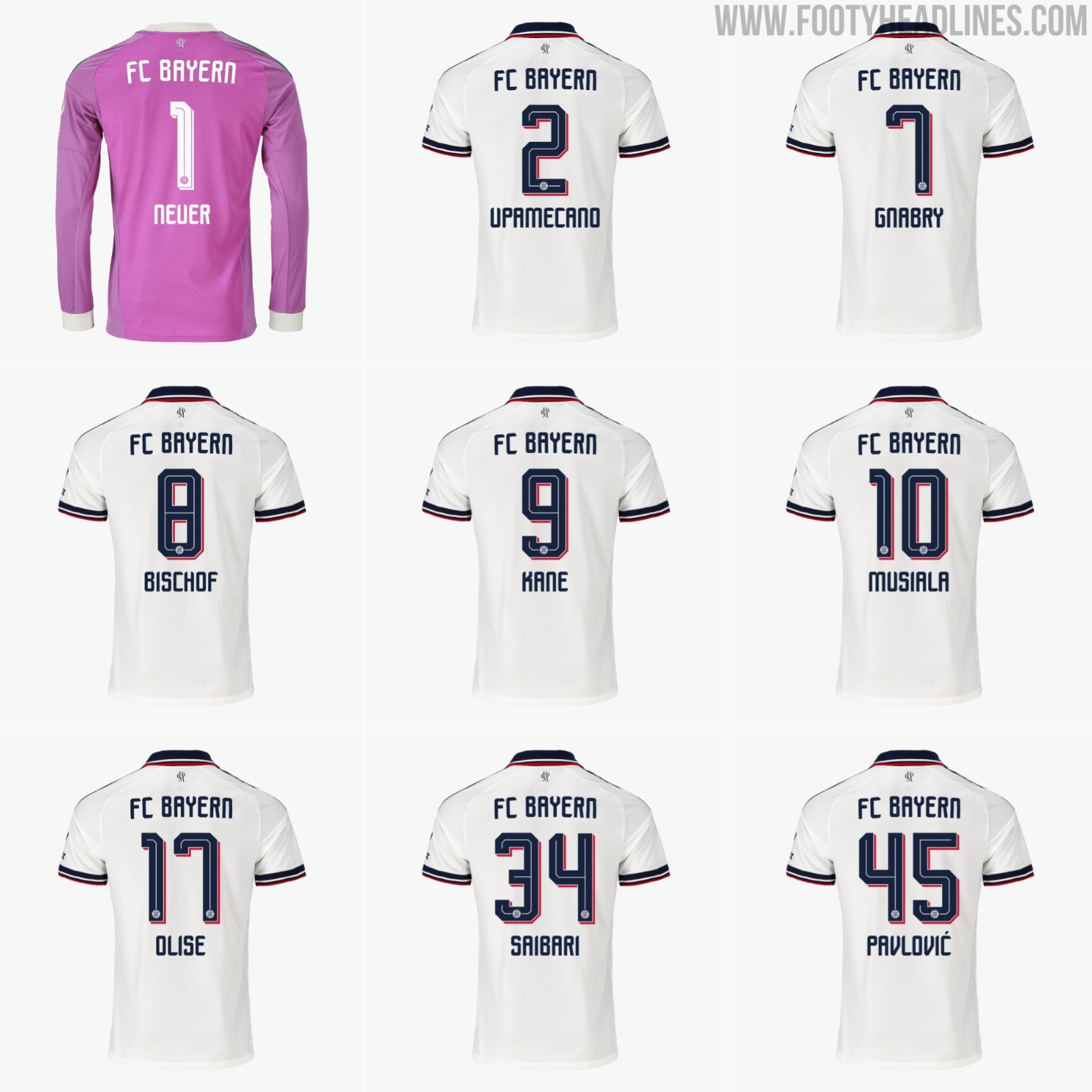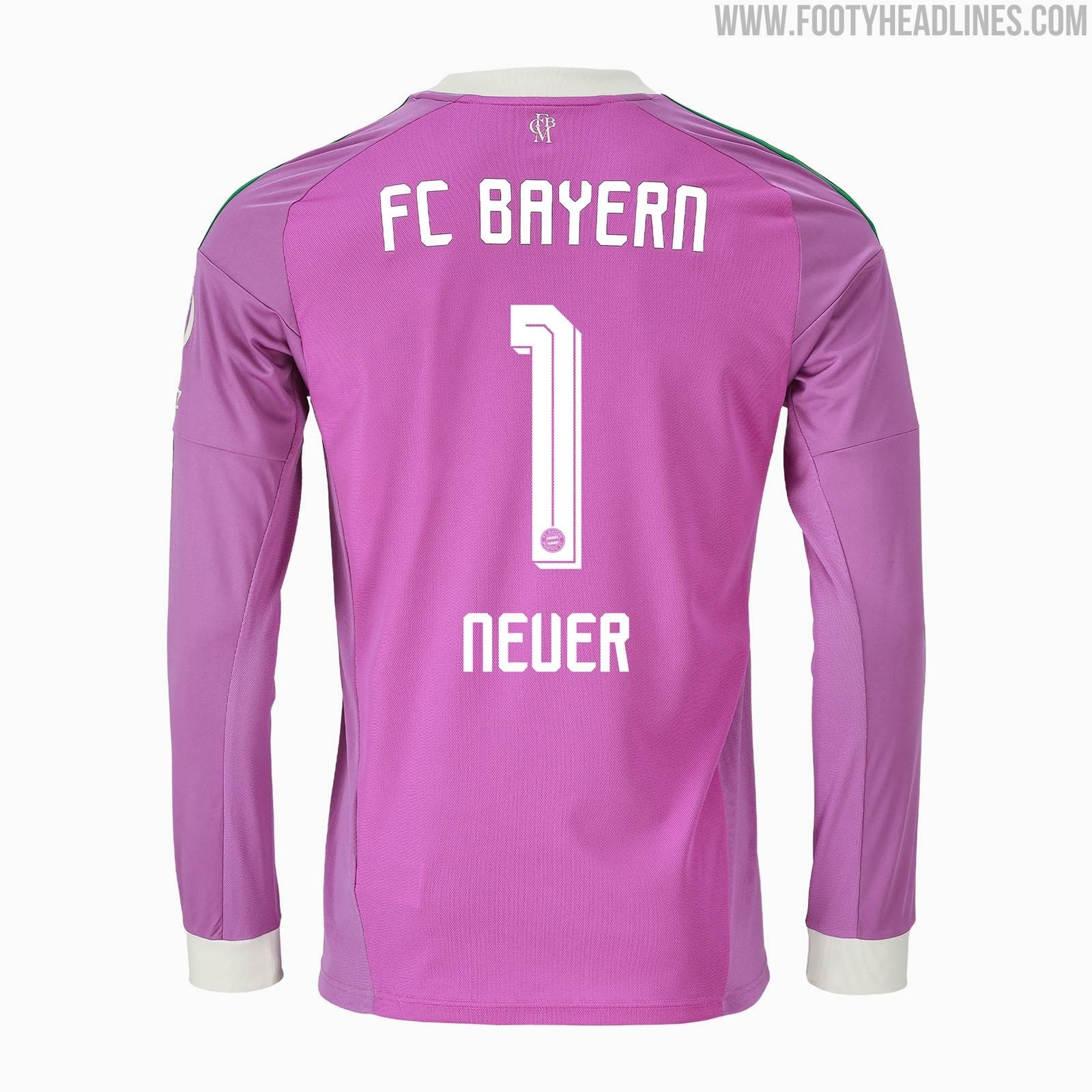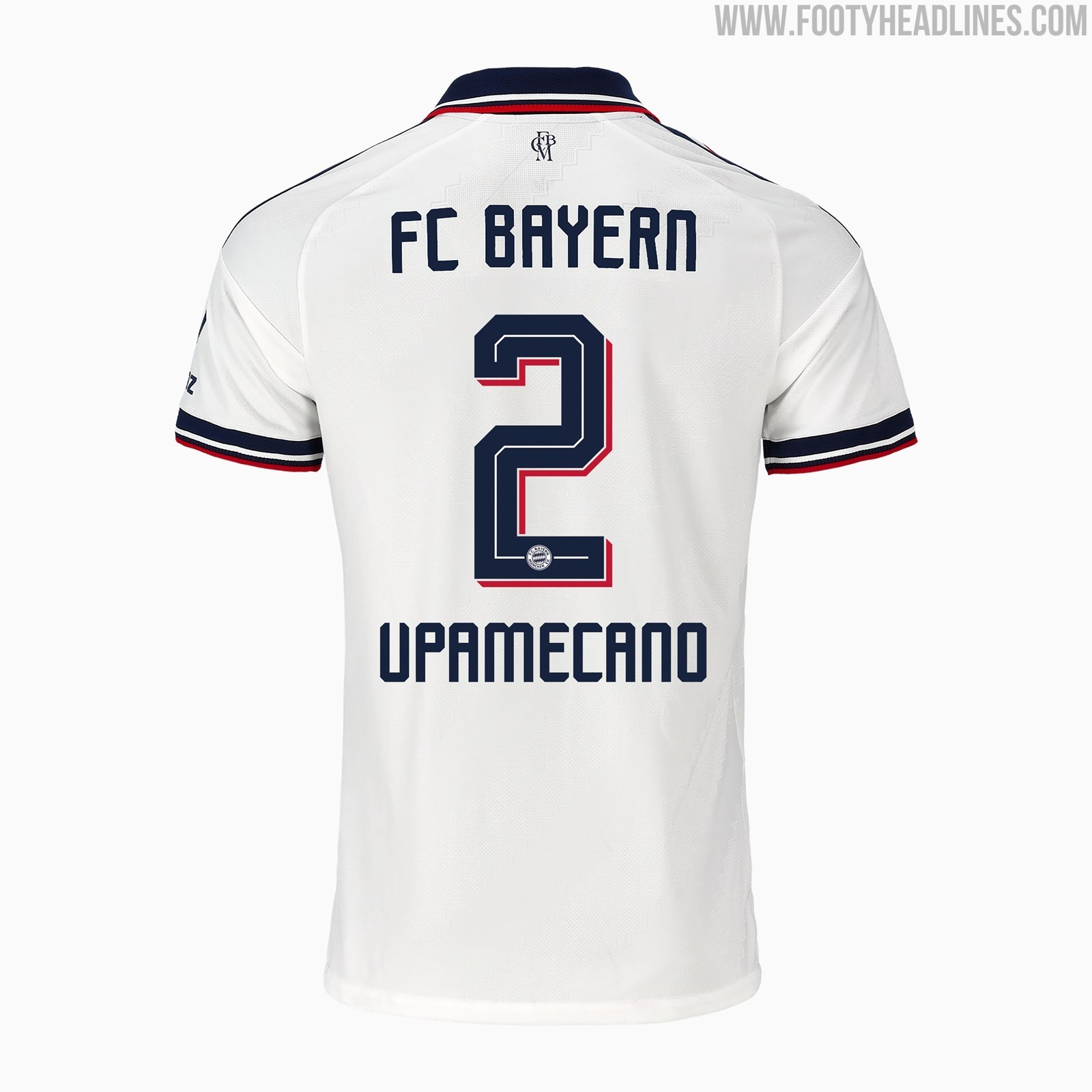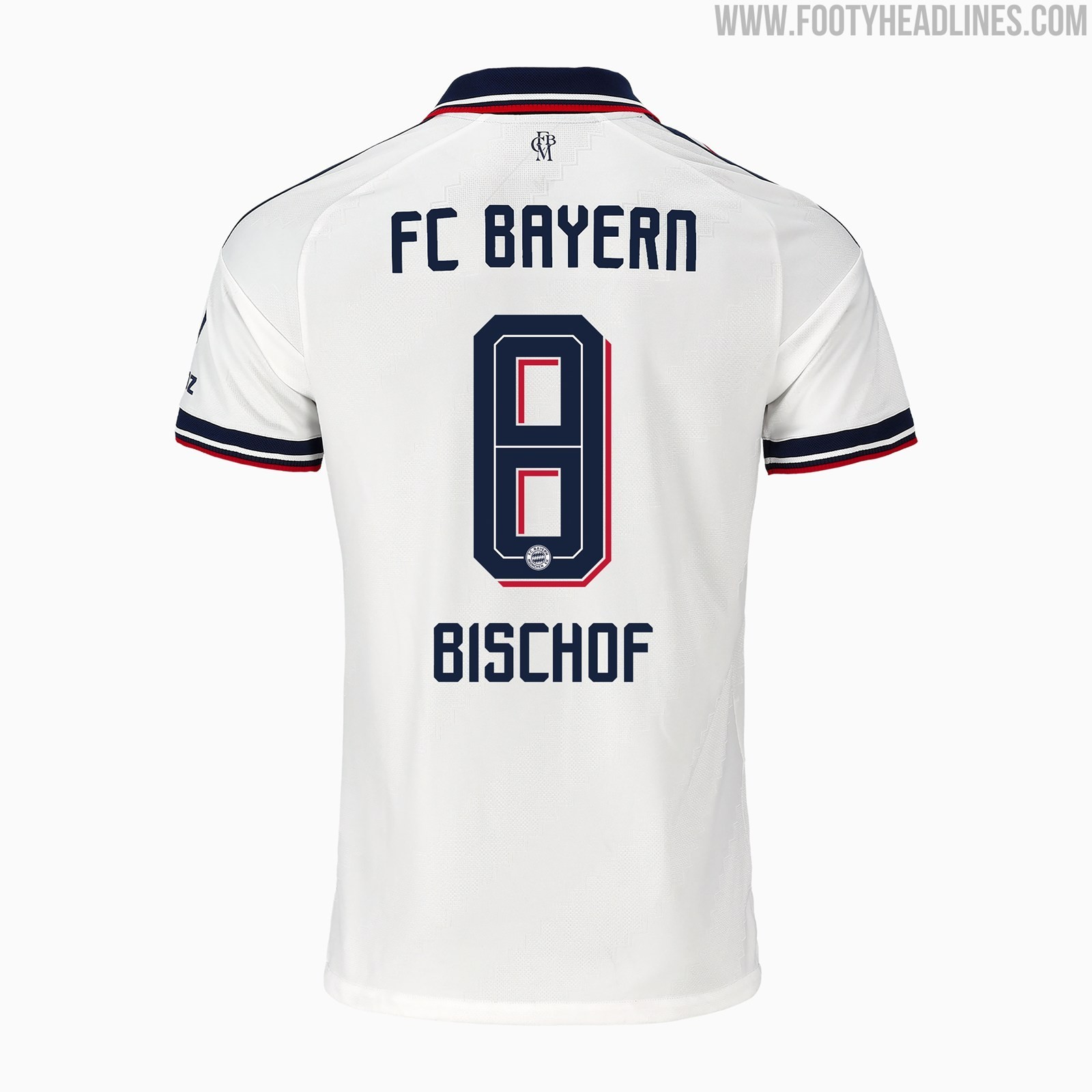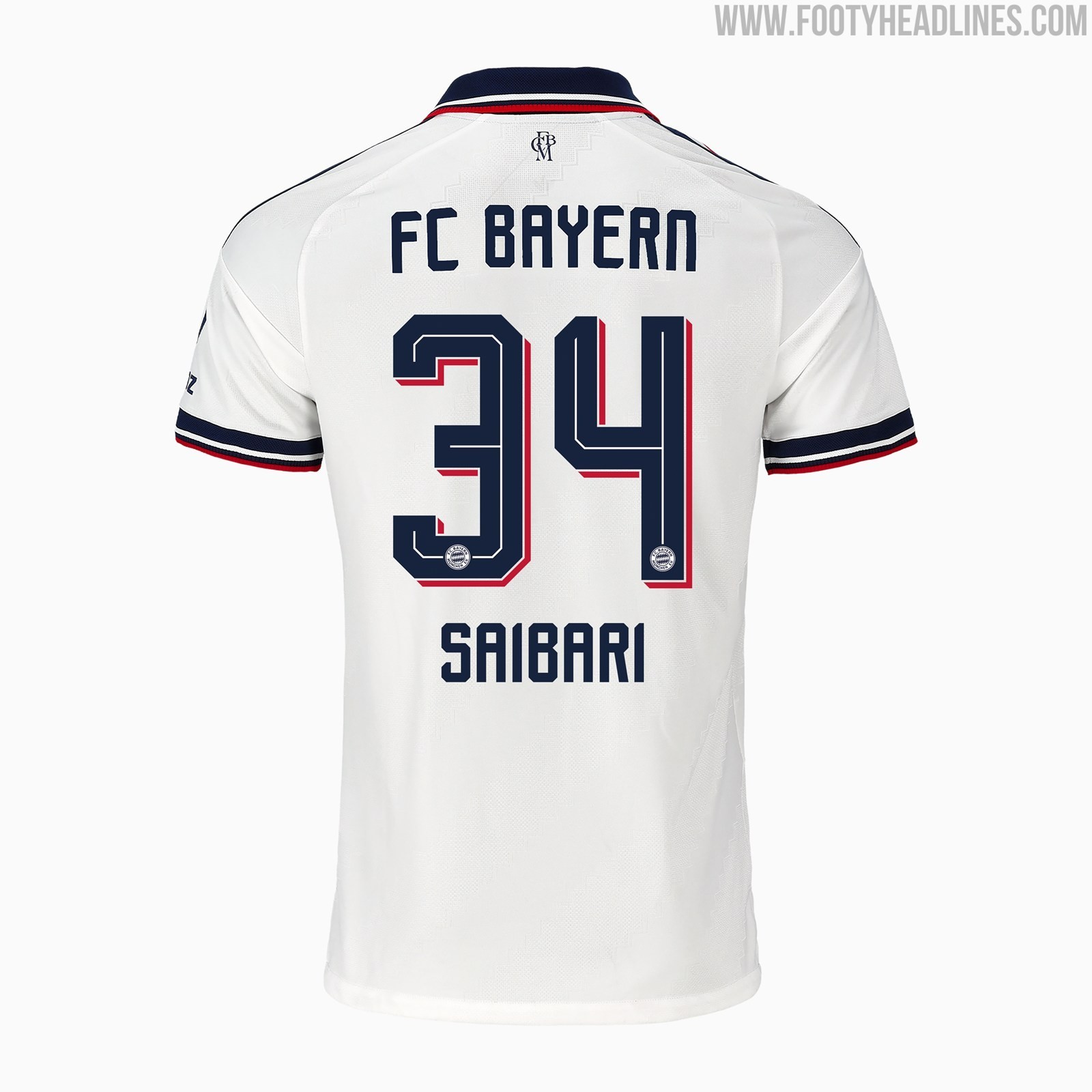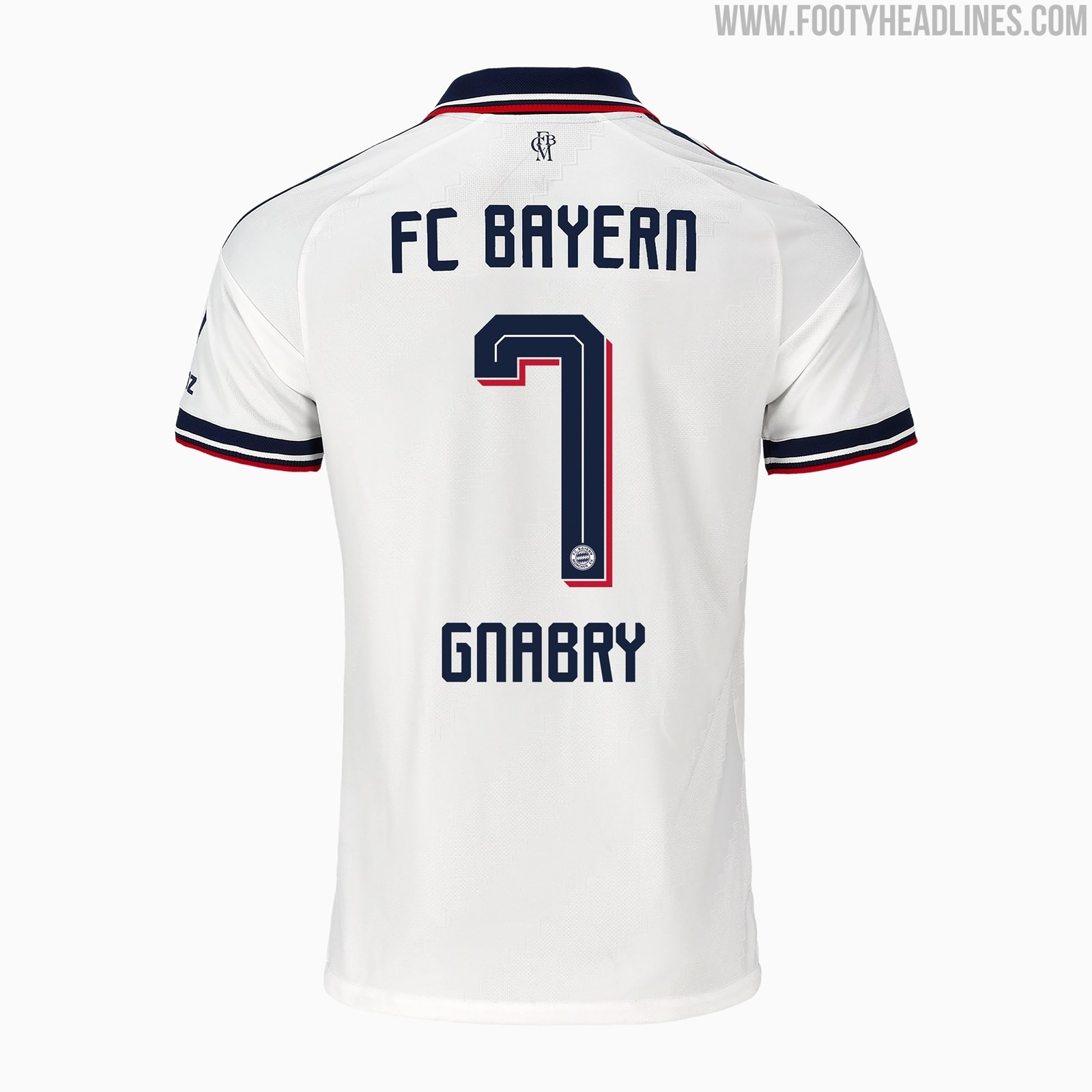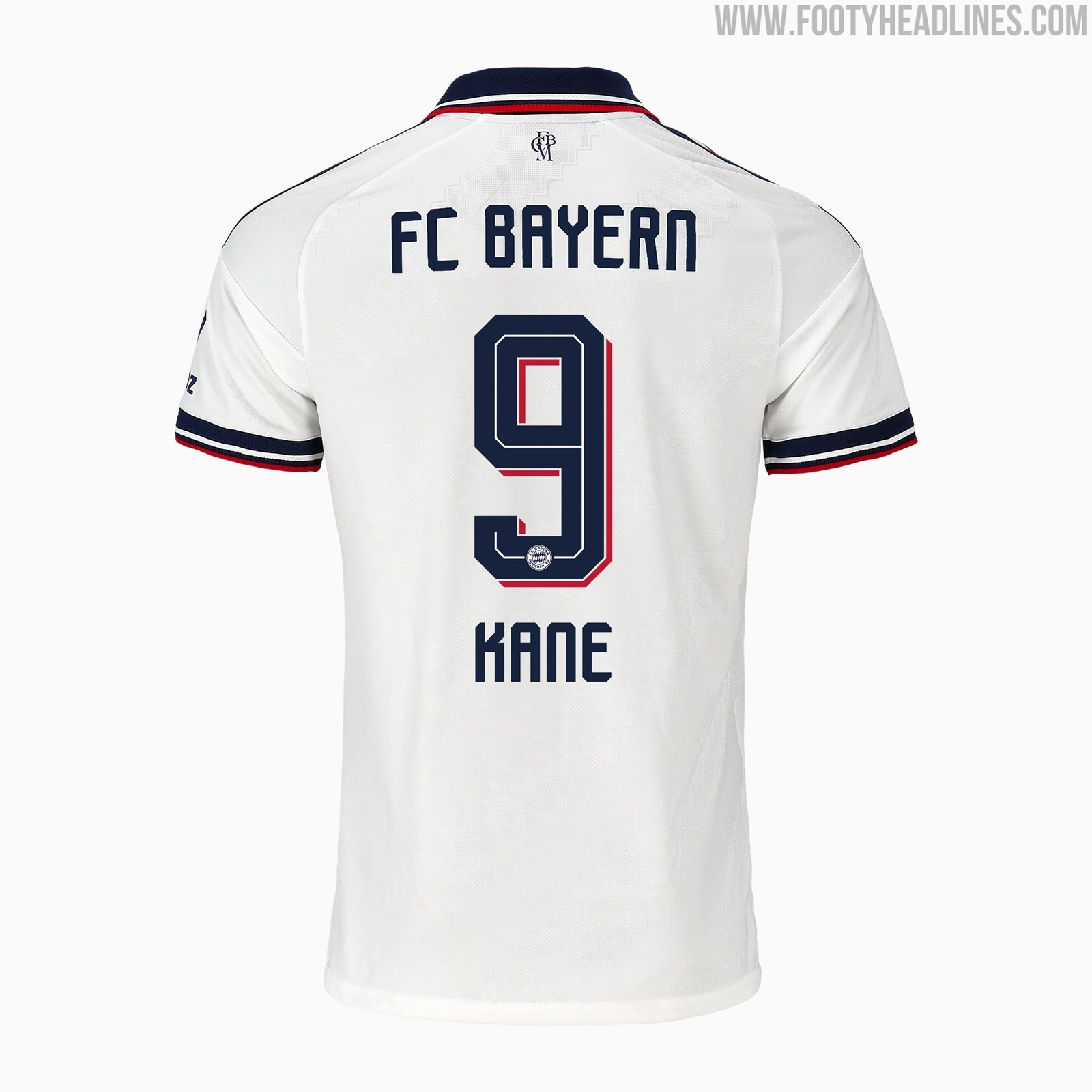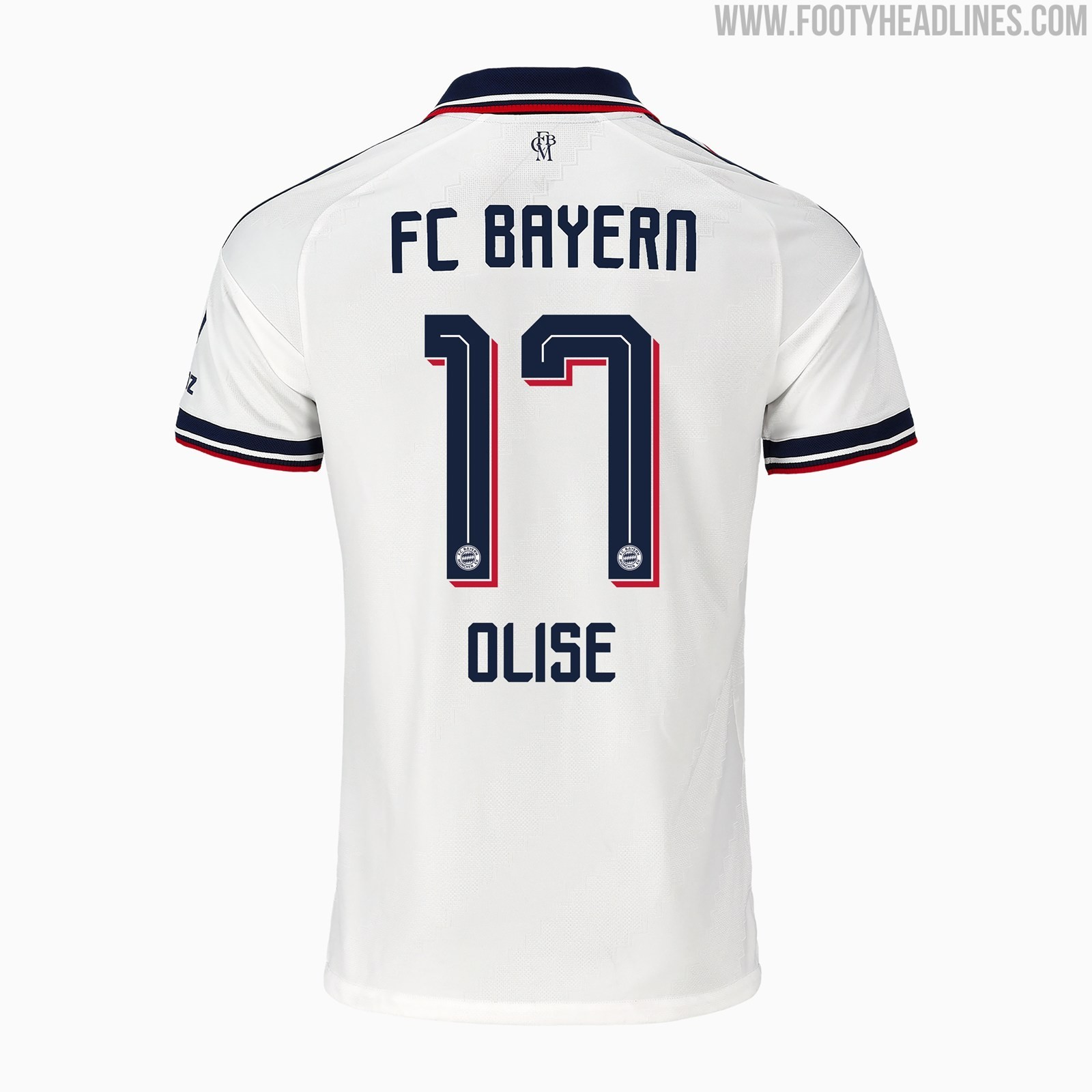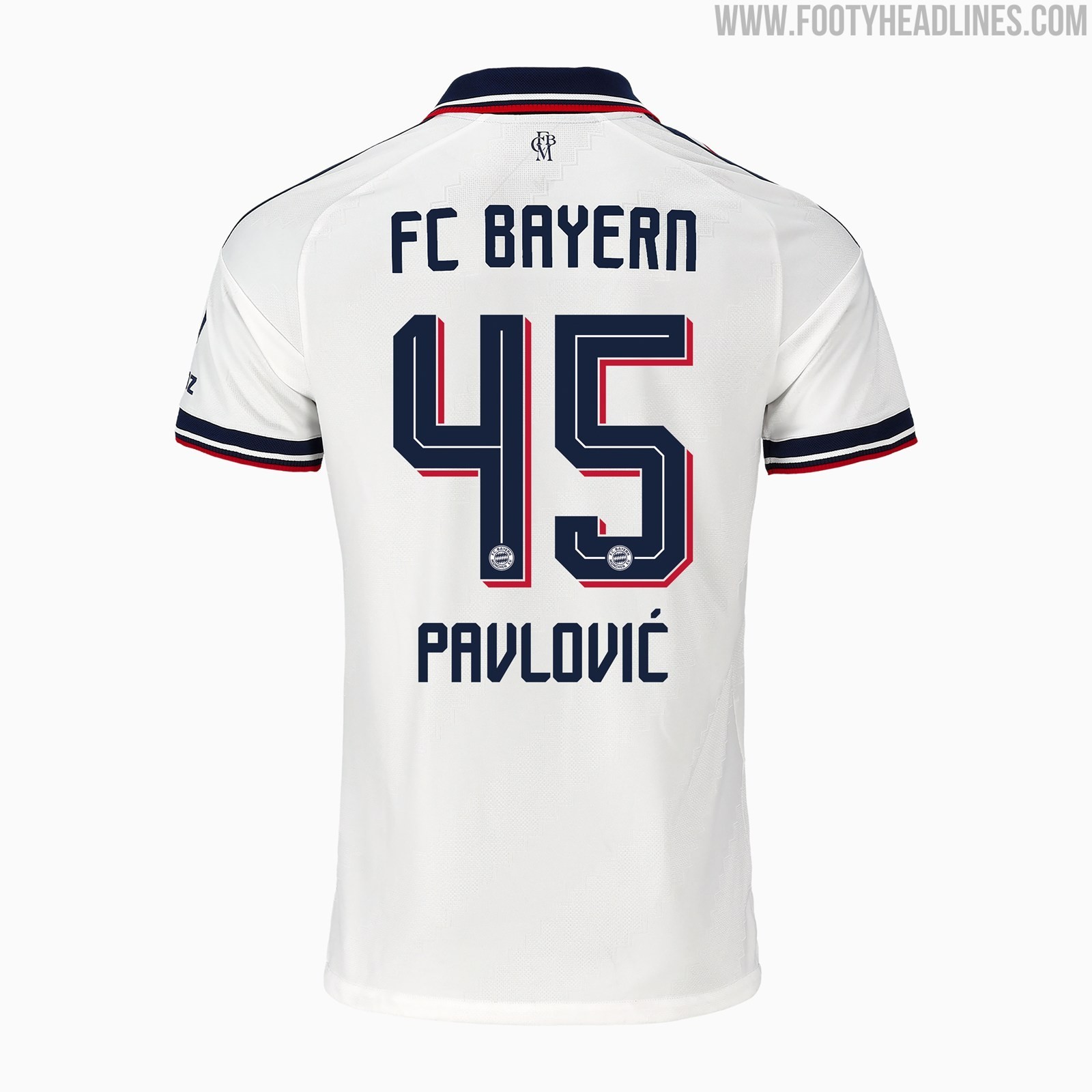
Se ha dado a conocer la tipografía de la camiseta visitante del Bayern de Múnich para la temporada 26-27
• Presentación de la Tipografía: Se ha desvelado la tipografía personalizada para la camiseta visitante del Bayern de Múnich de la temporada 26-27, la cual complementa un diseño retro.
• Características del Diseño de la Camiseta: La camiseta visitante es blanca con detalles en rojo y azul marino, incorpora el clásico escudo 'e.V.' y el logotipo del trébol de Adidas, con nombres y números de jugadores de inspiración retro.
• Similitud con la Tipografía de Adidas: La tipografía utilizada es casi idéntica a la simplificada 'Trefoil Standard' de Adidas para el Mundial de 2026, manteniendo su estructura clásica y cuadrada, pero con una adaptación de colores.
Tras el lanzamiento oficial de la camiseta visitante del Bayern de Múnich 26-27, te traemos un análisis completo de la tipografía personalizada que se ha usado en la nueva camiseta. La camiseta tiene un fondo blanco con detalles en rojo y azul marino, y destaca el regreso del clásico escudo del club «e.V.» junto al logotipo del trébol de Adidas. Los nombres y números de los jugadores en la espalda combinan a la perfección con esta estética de inspiración retro.
Se ha dado a conocer la tipografía de la camiseta visitante del Bayern de Múnich para la temporada 26-27
Tipografía de la camiseta visitante del Bayern de Múnich 26-27
La tipografía de la camiseta visitante del Bayern de Múnich para la temporada 26-27 es casi idéntica a la tipografía simplificada de Adidas para el Mundial de 2026, a la que a menudo se conoce como «Trefoil Standard».
Si comparas directamente una camiseta estándar de Messi con el logotipo «Trefoil» de Adidas y la nueva camiseta de Musiala, se nota que la tipografía es muy parecida. Usa exactamente la misma estructura clásica y cuadrada, con los mismos detalles en línea, pero adaptando la combinación de colores para que vaya a juego con el diseño azul marino y rojo del Bayern. El número 1, por ejemplo, tiene una pequeña diferencia en la parte inferior.